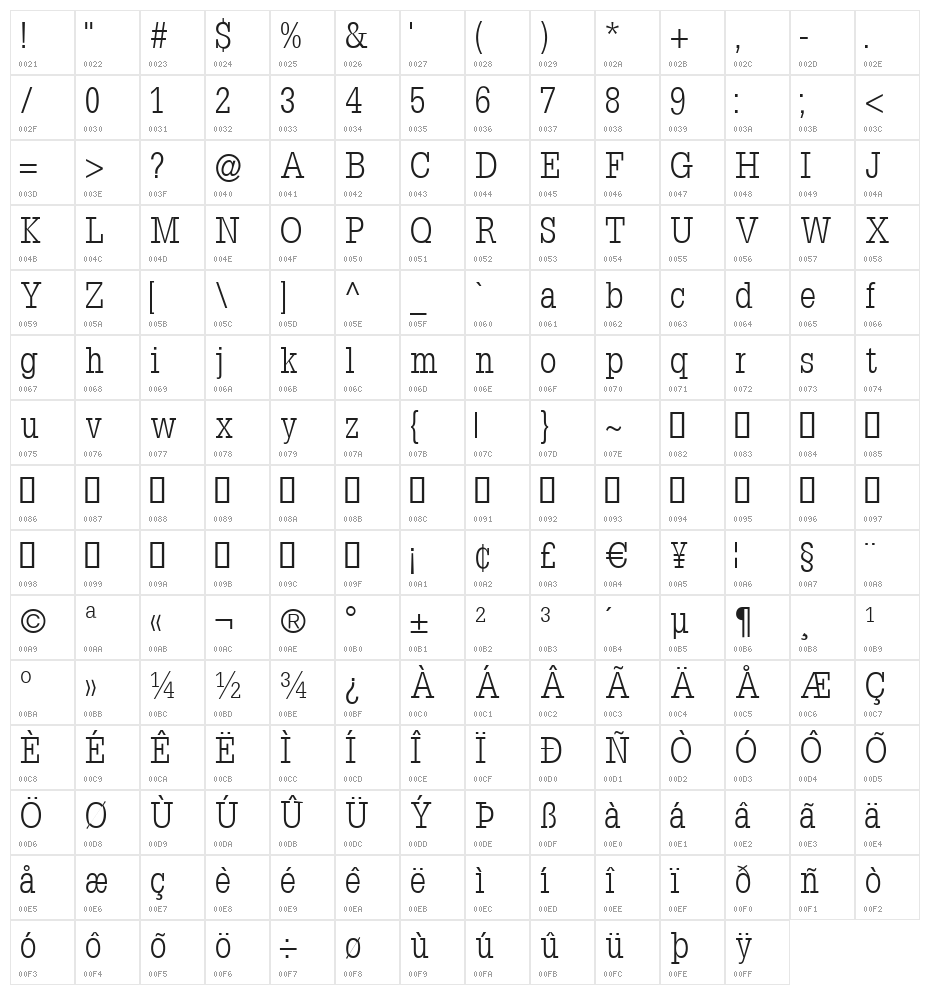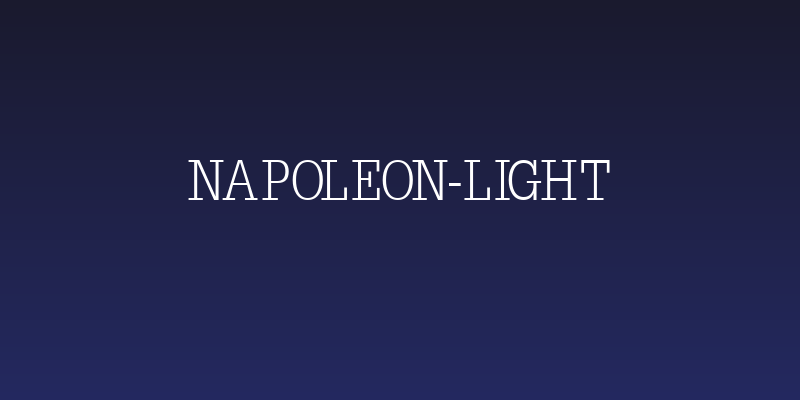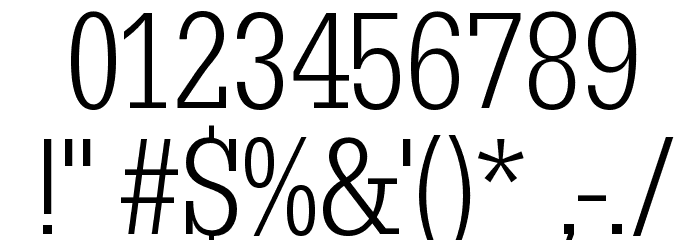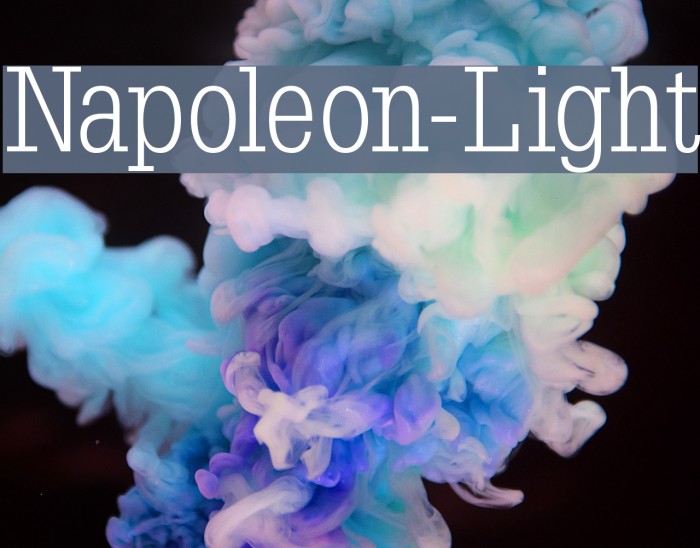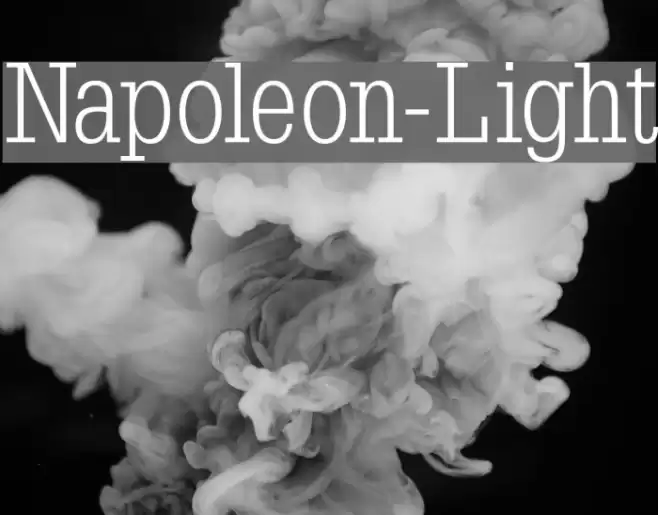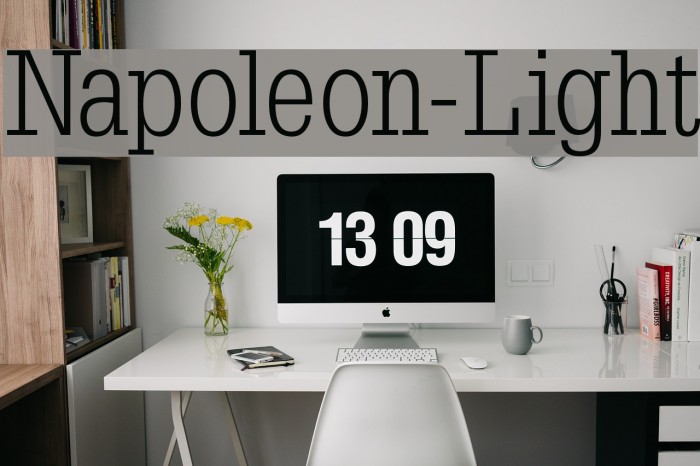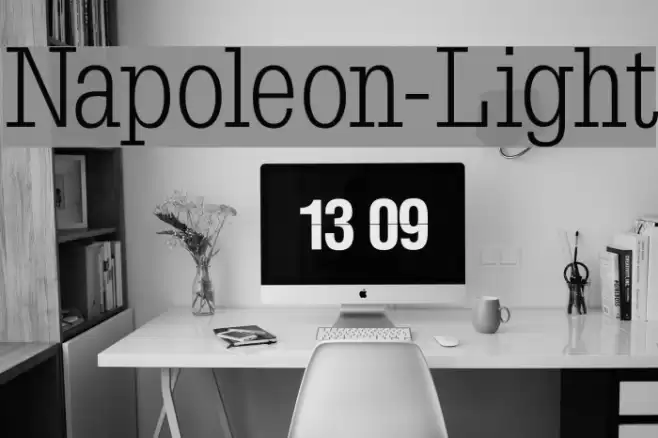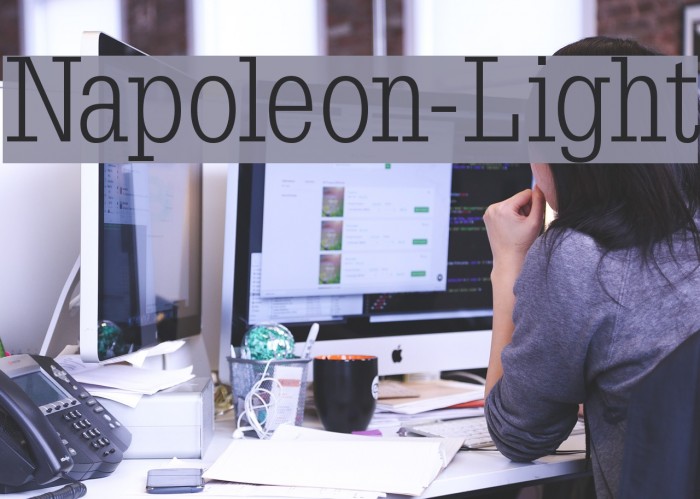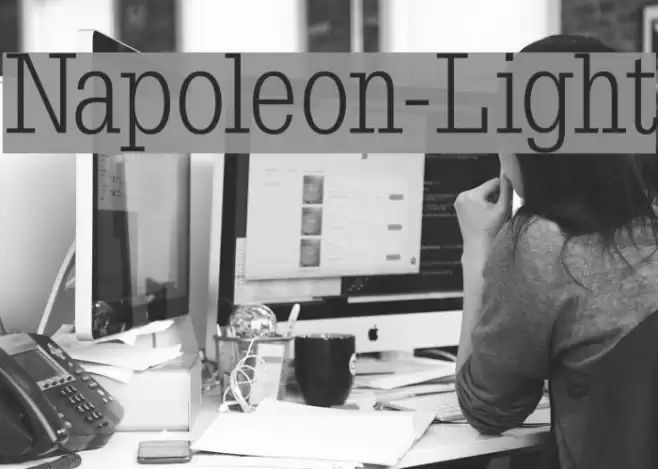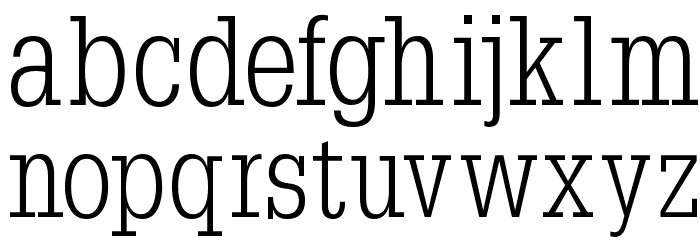
Napoleon-Light Font
✎ Serif
| Категория | Serif |
| Общий стиль | Classic |
| Область применения | Headlines, Body text, Logos |
| Рекомендуемые проекты | Ideal for editorial design, book covers, formal invitations, and branding materials that require a touch of elegance and readability. |